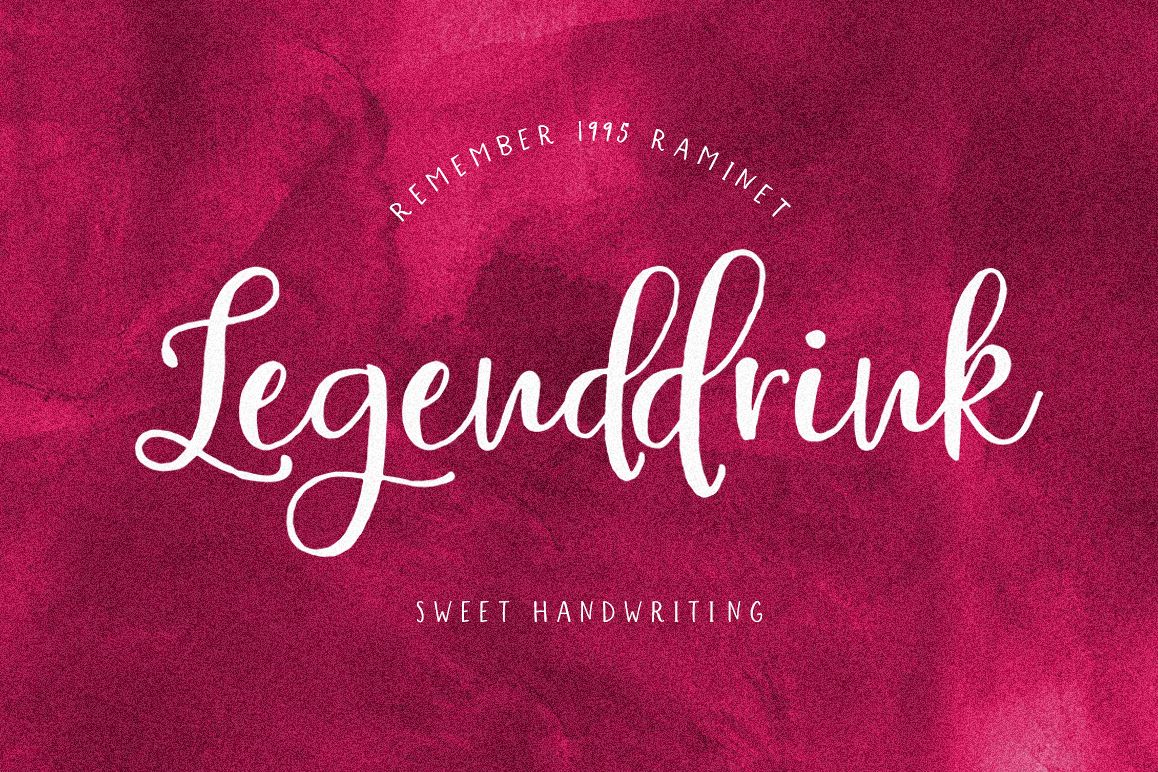
Legenddrink
Legenddrink-Regular
Legenddrink adalah skrip tulisan tangan modern, enerjik, organik, dan dinamis, dapat digunakan untuk berbagai tujuan.
seperti judul, korespondensi, logo, poster, lencana, undangan pernikahan, kop surat, papan nama, label, buletin tanda tangan, dll.
Legenddrink termasuk ligatures dan alternatif, dukungan internasional untuk sebagian besar Bahasa Barat.